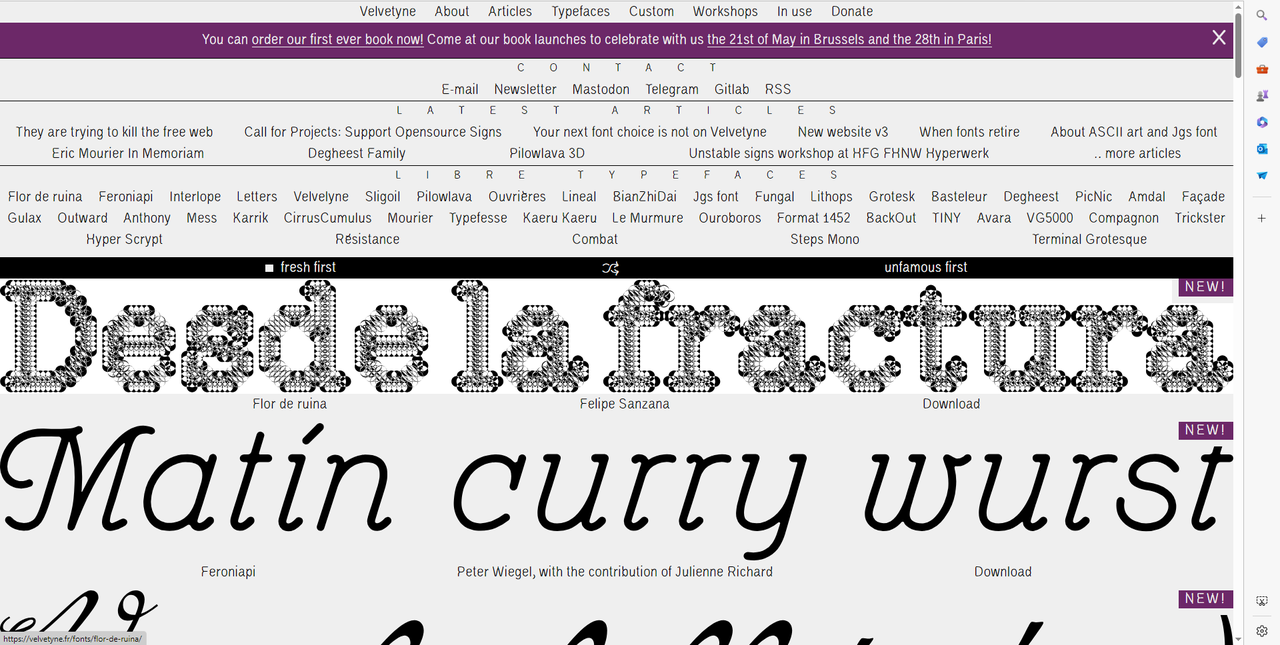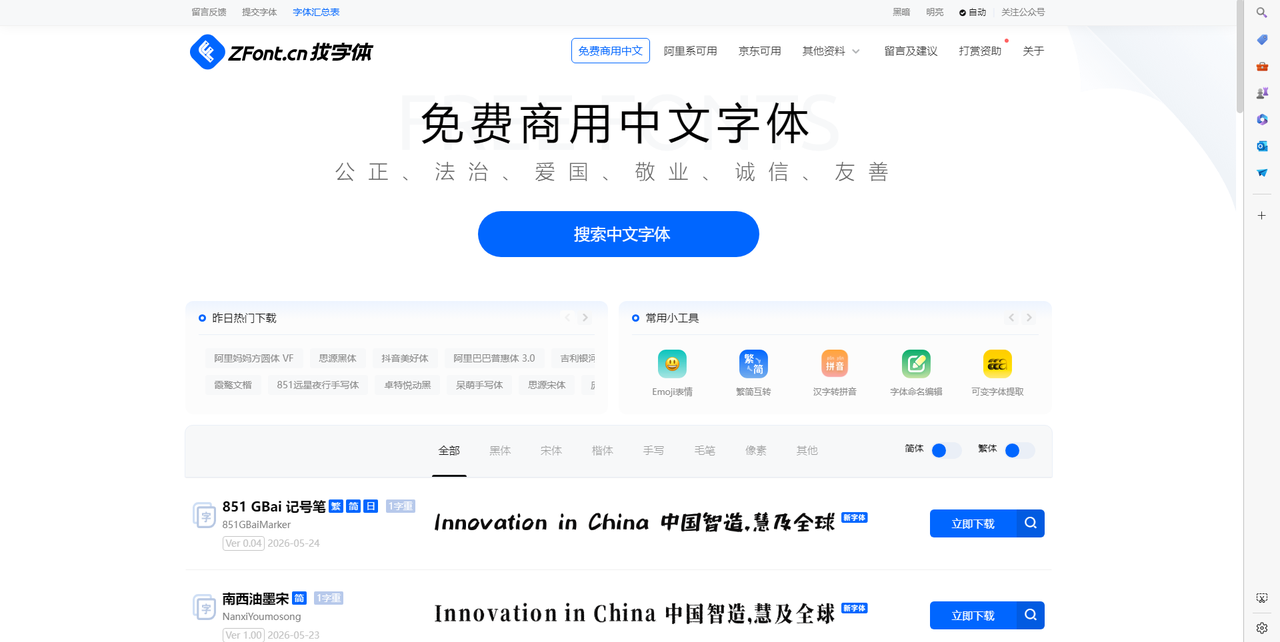
做设计项目时字体往往是基础素材,但好字体动辄几十上百美元一套,对自由设计师和小团队来说负担不小。其实有不少平台专门提供免费商用字体,来源正规、品质有保障,有些还是知名设计师或者字体工作室的作品。这篇文章整理的几个网站,有的主打设计师原创免费字体,有的专注开源字体社区,有的偏向中文字体资源,还有的是独立字体工作室的免费专区,找字体时比较省心。
字由在免费商用字体这块的积累比较扎实。客户端里的字体库有单独分类标注免费商用,勾选这个标签后,结果列表里就是全部允许商业使用的资源。对于做客户项目或者对外发布物料的设计师来说,这个筛选逻辑很省心,下载前不需要再去别的地方查授权状态,直接激活就能在设计软件里调用。目前收录的字体数量不少,其中免费商用字体的占比也在持续增加,经常能看到新上架的免费资源。
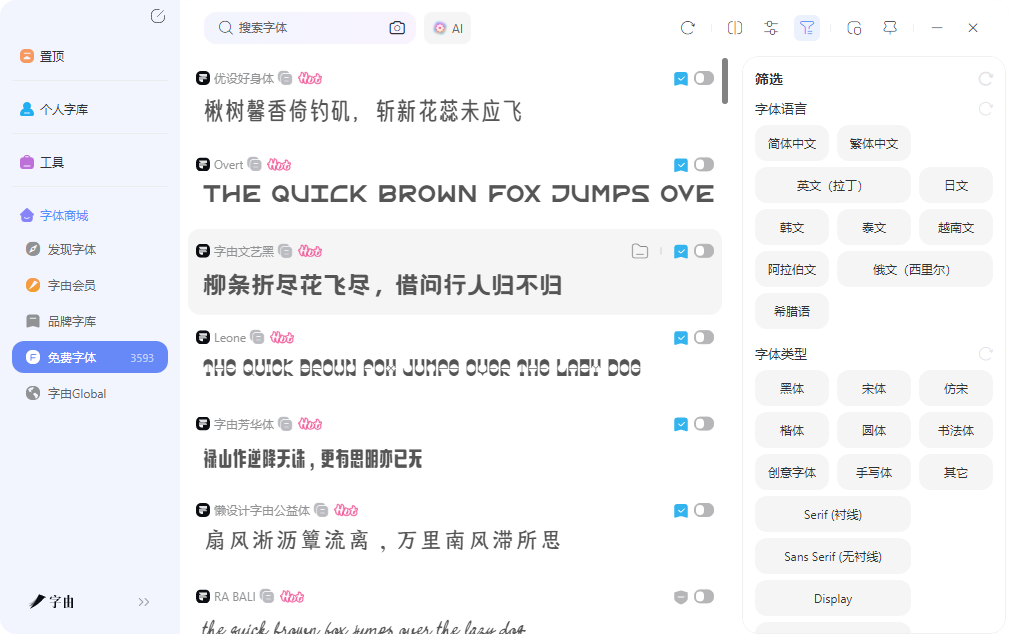
找字体时可以通过关键词搜索,输入"科技感"或者"复古"这类描述词,系统会返回风格匹配的字体列表,比按分类逐个翻页效率高不少。每款字体页面显示设计师信息、字重数量和授权状态,商用前确认清楚比较省心。对于做双语项目的人来说,可以筛选支持中文和拉丁字符集的字体,避免装完后发现英文显示不全的尴尬。
2、Velvetyne Type Foundry
Velvetyne是一个法国的独立字体工作室,网站上发布的字体全部免费商用,风格偏向实验性和创意性。字体设计大胆前卫,有些带有强烈的手绘感,有些则是几何切割的硬朗风格,适合需要视觉冲击力强的项目。对于做艺术海报、音乐专辑封面或者独立出版物的设计师来说,Velvetyne的字体辨识度很高,放在画面里很抢眼,和普通字体网站上的常规字体明显不同。
3、找字体网
找字体网是一个偏向中文字体的下载平台,收录的字体以国内设计师作品和经典中文字体为主。对于做中文项目、中文海报或者中文出版物的用户来说,这里的资源比纯西文字体网站更实用。网站按风格做了基础分类,黑体、宋体、楷体、仿宋、圆体各自有独立入口,找适合正式文档的字体时比较直接,不需要在杂乱的列表里翻找。
4、The League of Moveable Type
The League of Moveable Type是一个开源字体社区,运营了很多年,在设计师圈子里口碑不错。网站上收录的字体多为开源授权,个人项目和商业项目都能免费使用,有些字体还提供了源代码,可以自行修改和二次开发。对于需要深度定制字体的项目来说,这个开放度很有价值。比如做品牌设计时,可以在开源字体基础上调整某些笔画细节,做出更接近品牌气质的定制版本。
网站上的字体风格偏向经典和优雅,衬线体和无衬线体都有覆盖,适合出版物、品牌手册和正式文档。每款字体页面显示设计师信息、字符集覆盖范围和授权说明,选字体时更有依据。The League of Moveable Type的字体库虽然数量不如商业平台庞大,但收录的作品经过筛选,品质比较稳定,对于追求字体质量而不是数量的设计师来说,这里的资源比较对口。
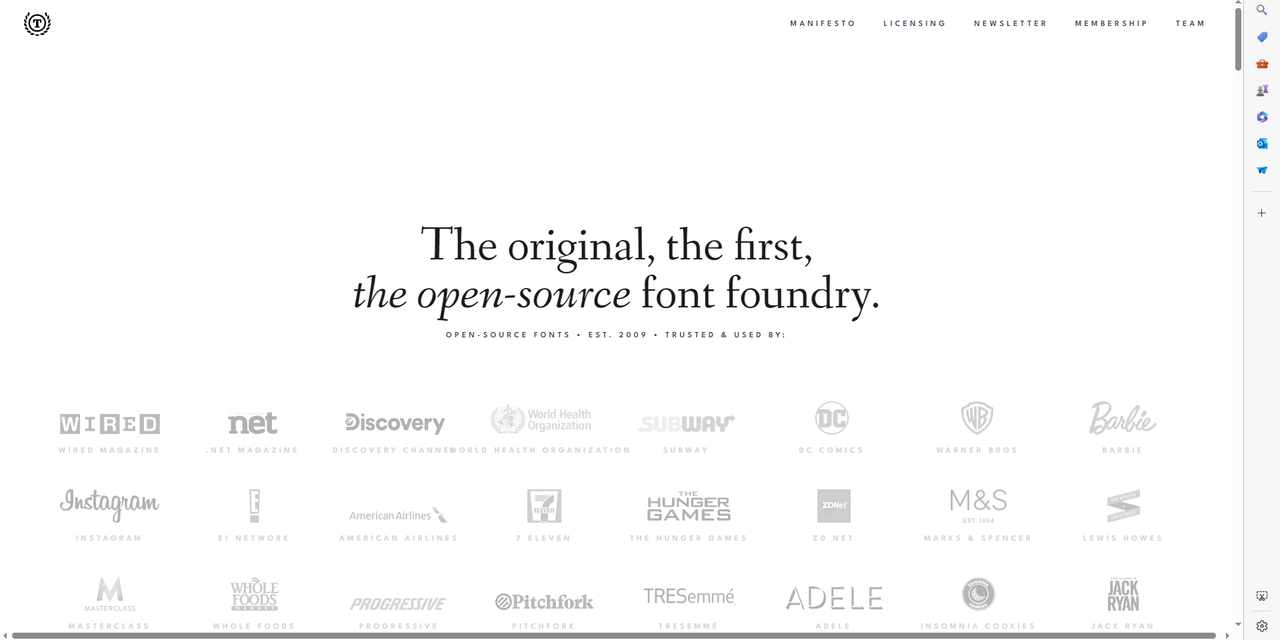
5、Fontshare
Fontshare是一个由印度字体公司Indian Type Foundry运营的免费字体平台,所有字体都经过专业设计,品质在免费字体里属于第一梯队。网站上的字体多为现代无衬线体和几何风格,适合品牌设计、网页排版和移动应用界面。每款字体都有完整的字重家族,从细到粗覆盖齐全,做标题和正文混排时层次感很好。有些字体还支持可变字重,在范围内任意调节粗细。
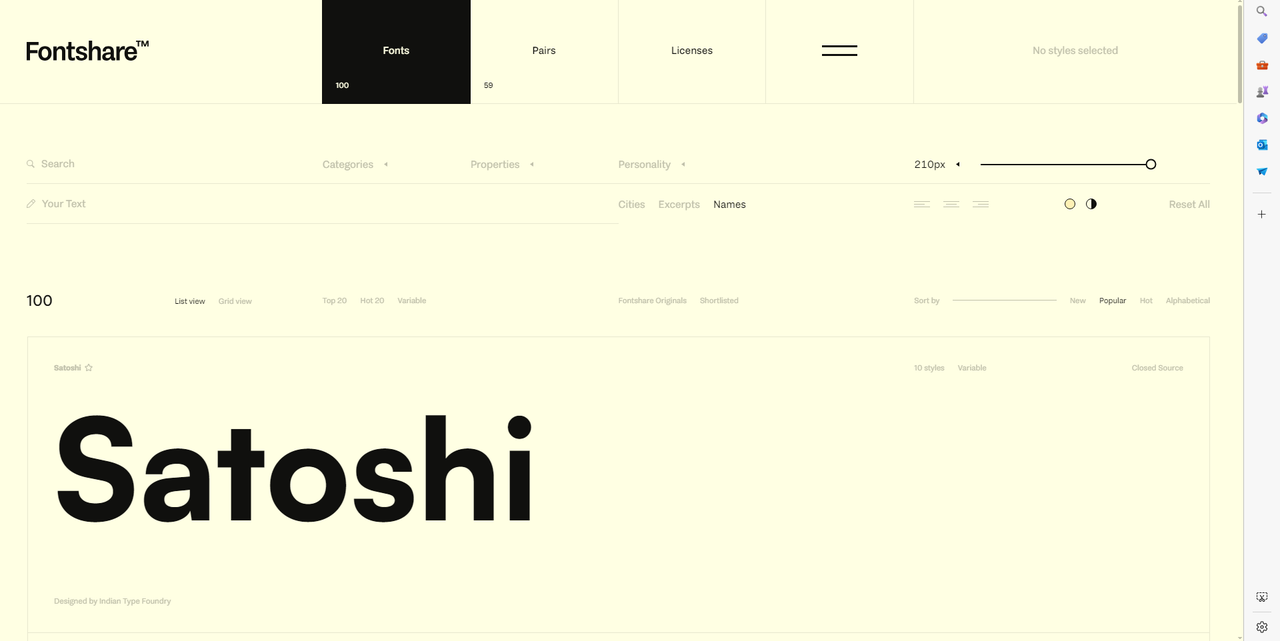
Fontshare的现代无衬线体适合品牌和网页设计,The League of Moveable Type的开源字体适合出版物和正式文档,找字体网的中文字体适合国内项目,Velvetyne的实验性字体适合创意和艺术项目。字由在字体管理和即时调用方面比较省心,从选字体到在设计软件里使用都能在客户端内完成。按自己的项目类型和语言需求来选,西文项目Fontshare和The League品质有保障,中文项目找字体网比较对口,想尝试前卫风格Velvetyne值得收藏。